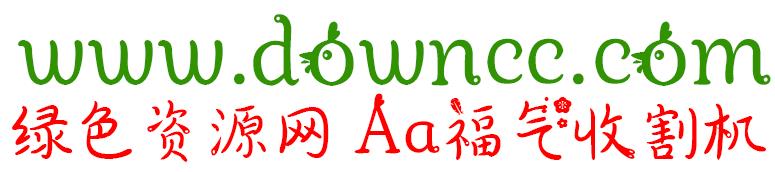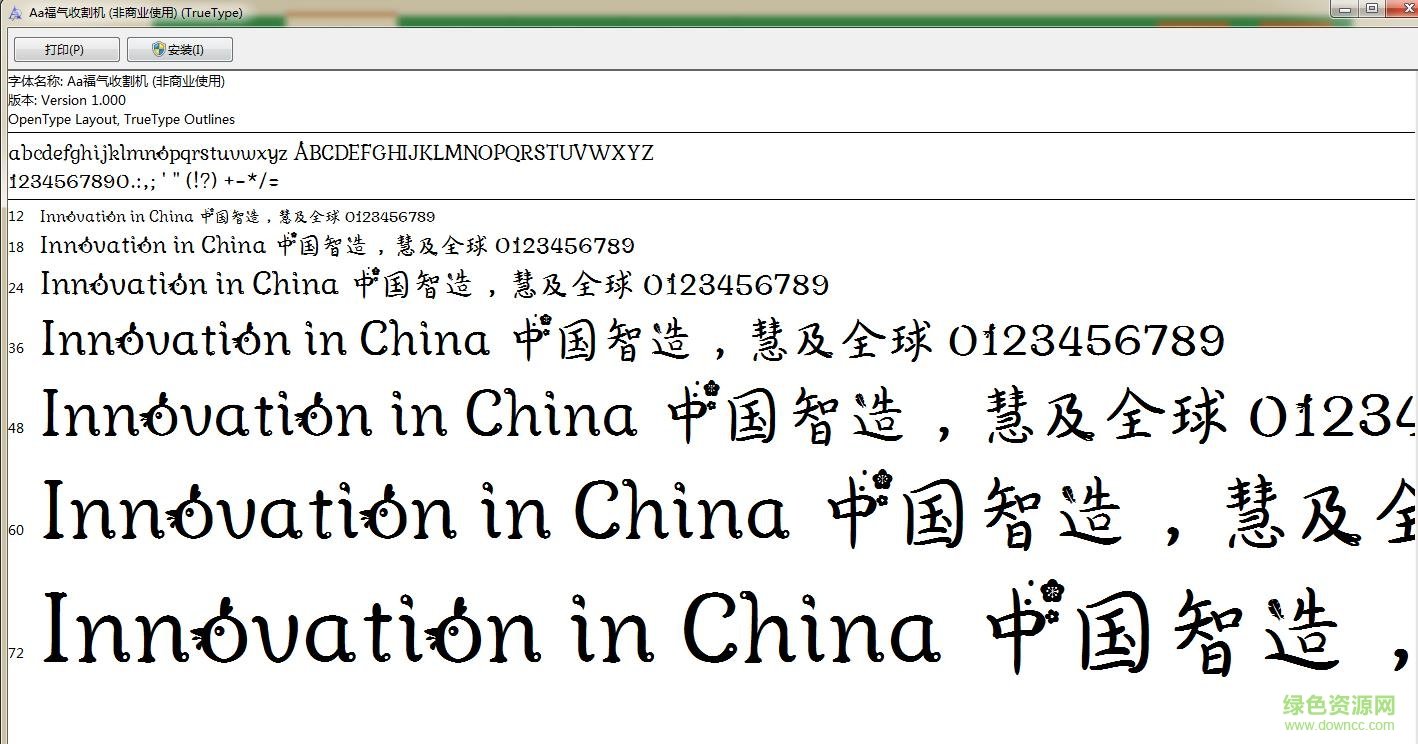
Aa福氣收割機字體這款字體每一個字體都擁有十分喜氣的感覺,讓你在使用的時候將感受到不錯的視覺使用效果,字里行間都流露出一種喜氣洋洋的感覺,就像過春節(jié)一樣福氣滿滿,快來綠色資源網(wǎng)下載吧!
這款字體在進行色彩變幻之后變得十分好看,同時如果變成紅色的字體的話就會十分喜氣洋洋哦,這款字體用著十分舒適,很好看!